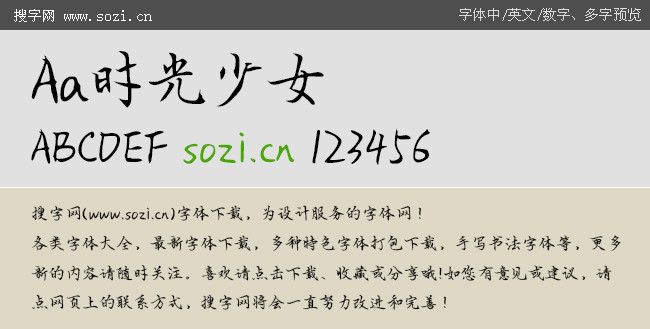
Aa時(shí)光少女
搜字網(wǎng)給大家提供一款A(yù)a時(shí)光少女字體中文字體下載,這是一款手寫風(fēng)格的書法字體,字體書寫自如,效果瀟灑大方,適合海報(bào)設(shè)計(jì)、包裝畫冊等宣傳廣告等應(yīng)用(此字體為個(gè)人非商用版,如需商用請聯(lián)系作者購買版權(quán))。